「歌ってみた」や「イラスト系のミュージックビデオ(イラストMV)」では、たくさんの素敵なフォントが使われていますよね。
かわいい/ポップ
筑紫A丸ゴシック(Fontworks/Adobe Font)
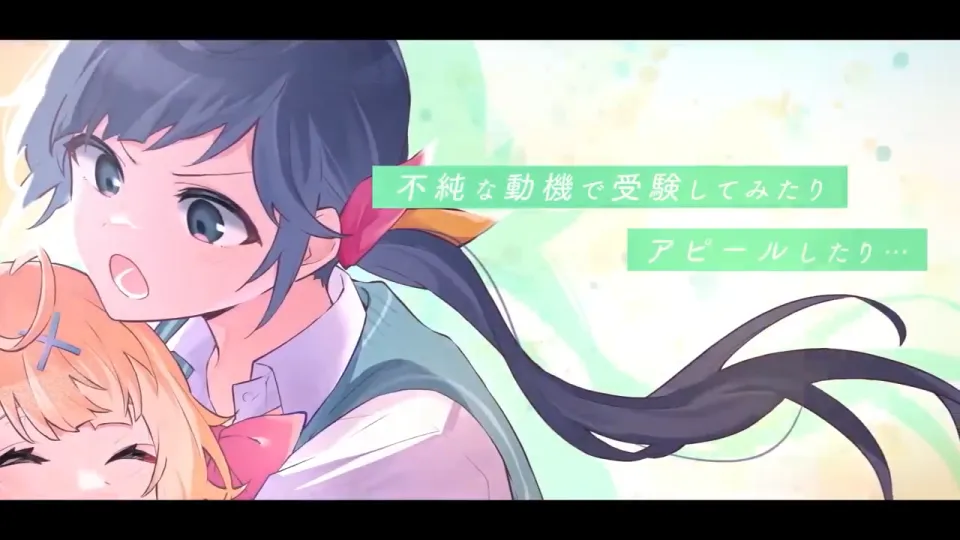
読みやすくて温かみのある丸ゴシック体フォントです。
ベビポップ(Fontworks/mojimo)
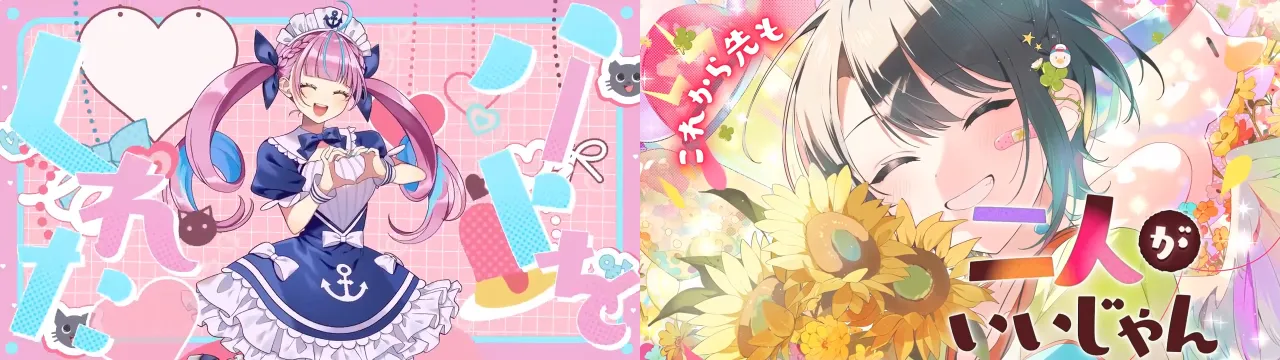
太くて幾何学模様っぽいシルエットが特徴の『元気』な印象を与えてくれるフォントです。
パルラムネ(Fontworks/mojimo)
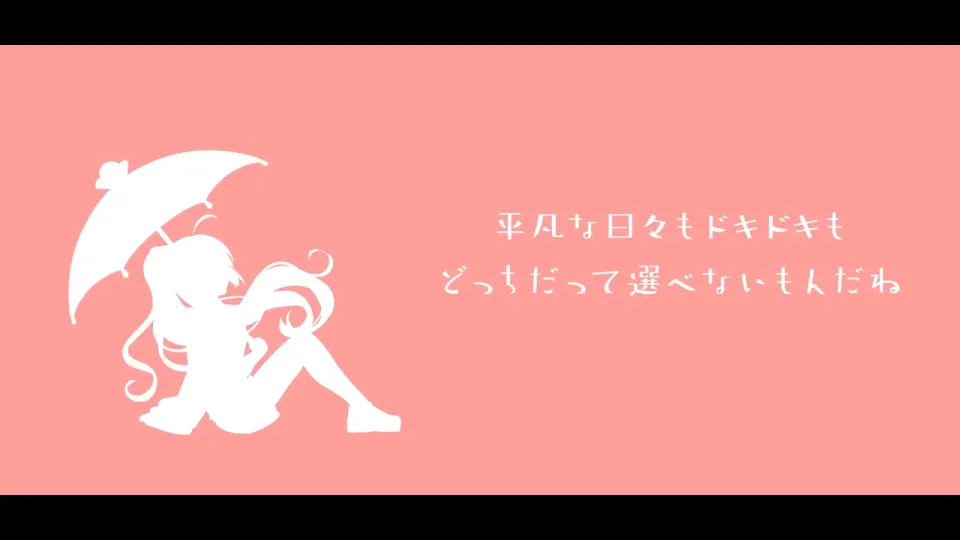
カクっとした中にゆるさとリズミカルさを併せ持つフォントです。こちらもサブスクの「mojimo-manga」に収録されています。
めもわ〜る+にくまるフォント(MODI工場/フロップデザイン)
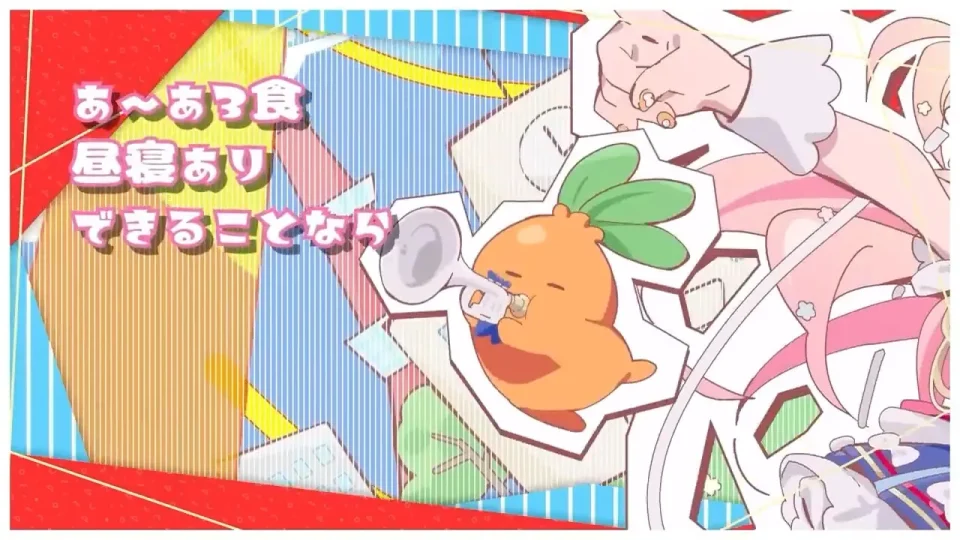
ファンシーでポップな「めもわ〜る」と、漢字部分を「にくまるフォント」にした組み合わせです。
モッチーポップ(FONTDASU)
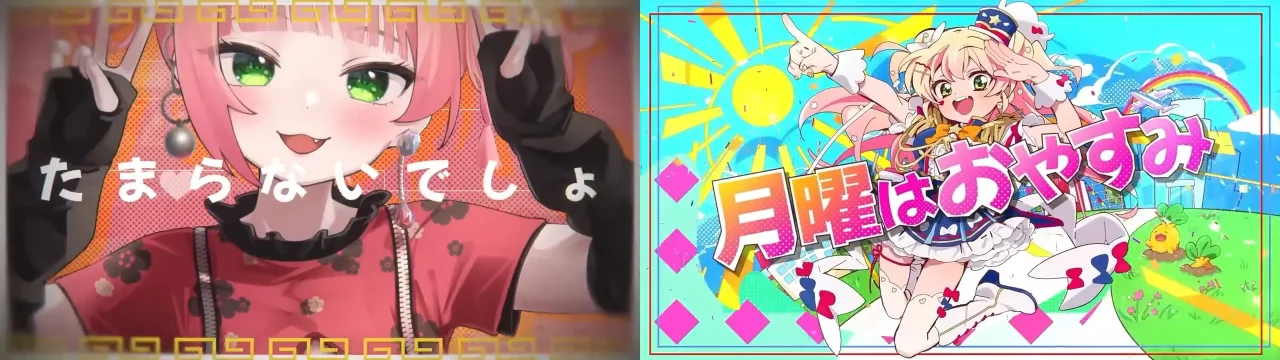
FONTDASUさんの適度な丸さと視認性を持ったかわいいフォントです。
ラノベポップ(フロップデザイン)
「入り」や「ハネ」のカクカクが特徴的なかわいいフリーフォントです。
けいふぉんと!(すもももじ)
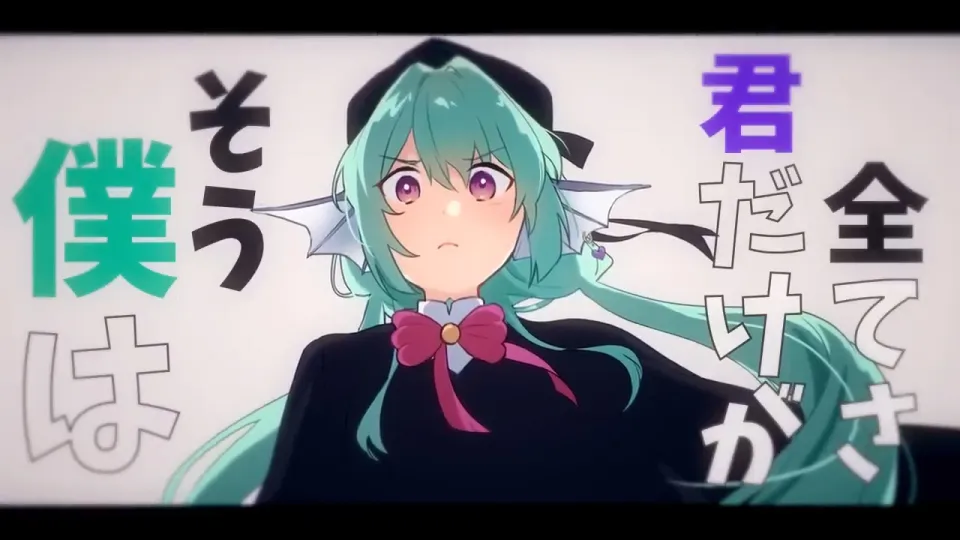
アニメ「けいおん!」のロゴにインスパイアされて製作されたフリーフォントです。
JKゴシック(ふぉんときゅーとがーる。)
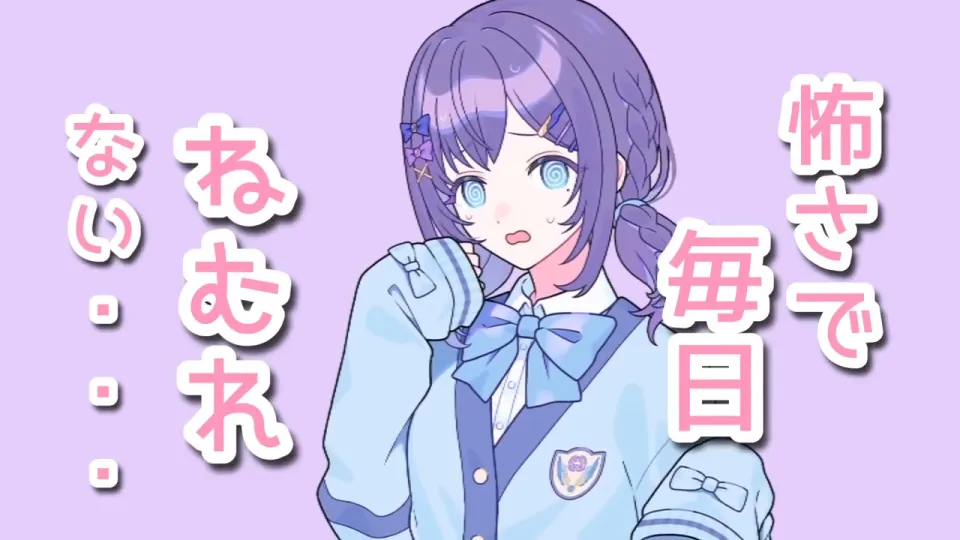
女子高生が書いたようなかわいいフリーフォントです。
JK丸ゴシック(ふぉんときゅーとがーる。)
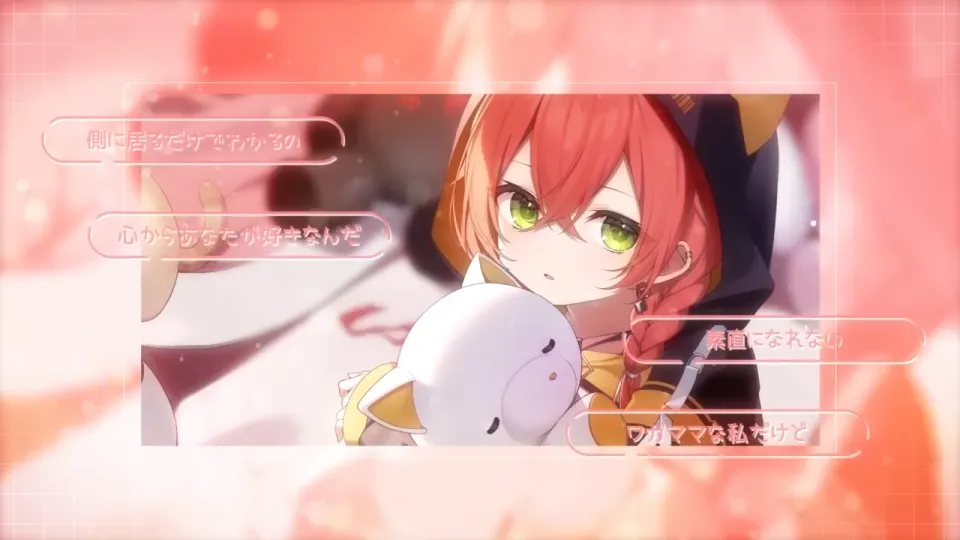
角が丸く柔らかい雰囲気のフリーフォントです。
こまどり(ヤマナカデザインワークス)
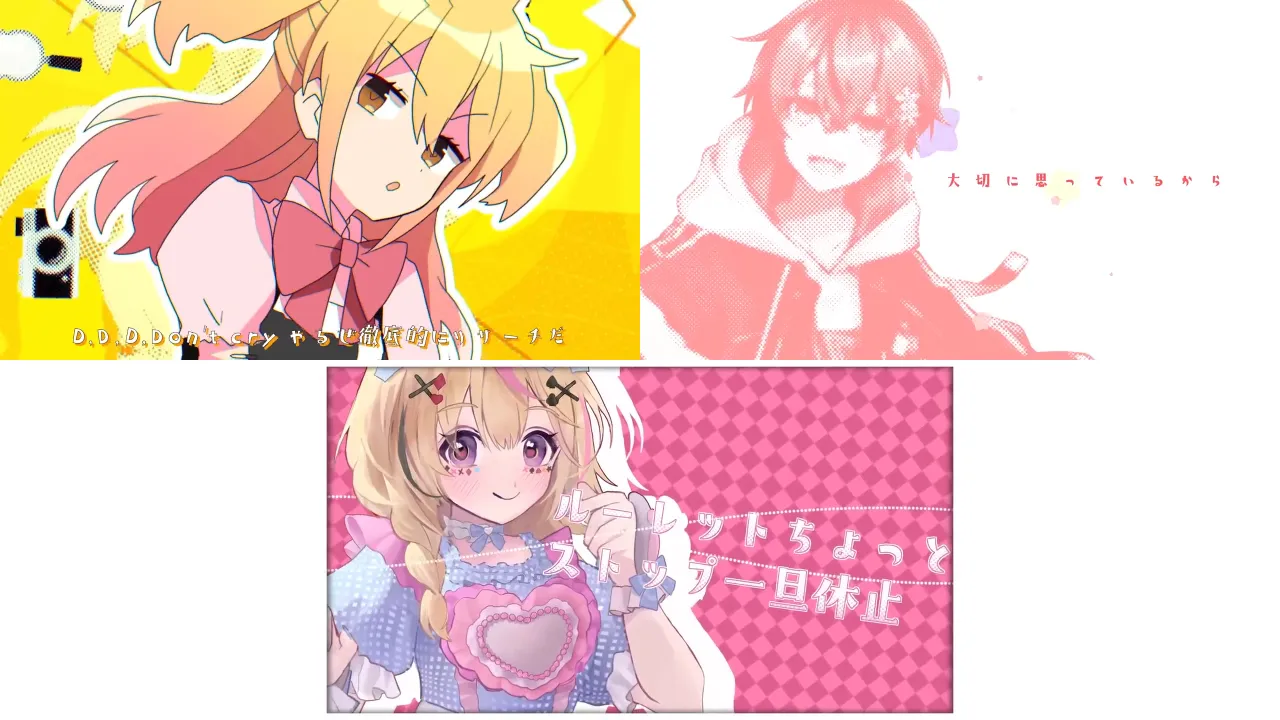
可愛らしいカクカクっとしたフォントです。無料のmini版には80種類の漢字を収録されています。
かなりや(ヤマナカデザインワークス)
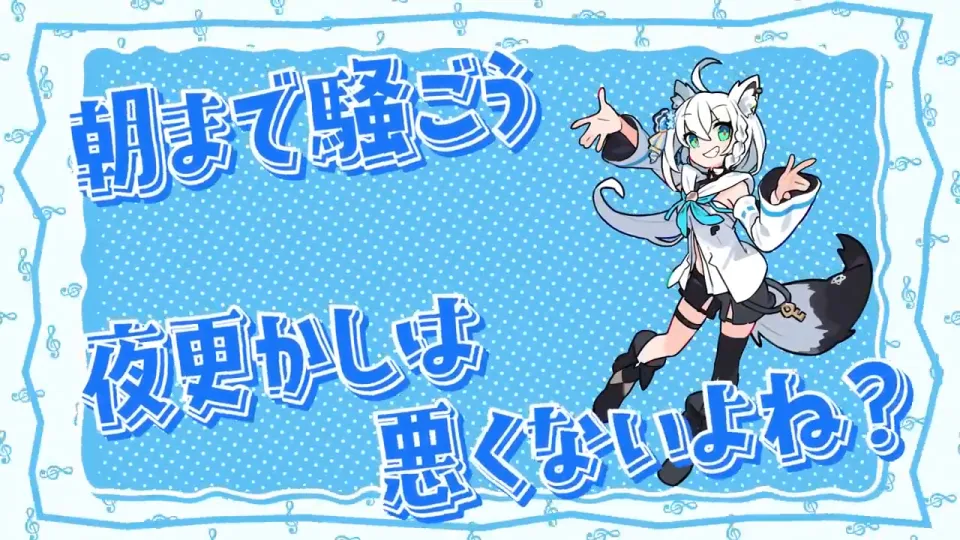
カクカクっとしたシルエットとウロコ・線の強弱が特徴的なフォントです。無料のmini版には80種類の漢字を収録されています。
つばめ(Fontworks/mojimo)
『つばめ』のように丸く、クチバシのようにとがった部分が印象的なかわいいフォントです。Fontworksの36種類のフォントが使えるサブスク「mojimo-manga」に含まれています。
ABマユミンウォーク(Adobe Font)
自由でリズム感を感じるかわいいフォントです。ほぼ同様のフォントでモリサワの「はるひ学園」があります。
ABキリギリス(Adobe Font)
多くのデザインで見かける、シャープでかわいいフォントです。こちらもAdobe Fontの中に含まれています。
やわらかドラゴン(ヤマナカデザインワークス)
インパクトと可愛さがセットになった視認性のいいフォント。無料版は240字の漢字が収録されています。
パンダベーカリー(鈴木メモ)
太くてカクカクっとした感じがかわいいフォントです。「シナぷしゅ」などのキッズ系の番組に使用されることも多いです。
ププ ピクニック(モリサワ)
太くてカクカクっとしたフォントです。「パンダベーカリー」と似ていますが、「は」や「け」などのハネがなく、すっきりとした元気な印象のフォントです。
うさぎと満月のサンセリフ(TYPING ART)
頭でっかちで丸っとしたシルエットが特徴的なかわいいフォントです。漢字の少ないお試し無料版と、ひらがな、カタカナ、英数字、常用漢字+α(2145文字)を収録した有料版の2つがあります。
すずむし(モリサワ)
まるっとした、墨溜まりやカーブが特徴的なフォントです。
あおかね(Fontworks/mojimo)
カクっとしたラインを持ちながらも先端は丸いといった、どことなく親しみを感じさせるフォントです。サブスク「mojimo-jewel」に収録されています。